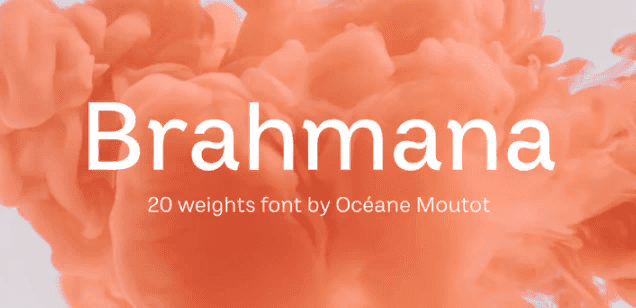
Название: Brahmana Font (2021)
Brahmana - это современный шрифт sans serif, отличающийся игривостью и оригинальными деталями.
Его большая высота x-height обеспечивает этому дружелюбному линейному шрифту разнообразие для использования, от заголовков, издания текстов, брендинга, журналов и так далее. Большое разнообразие глифов, включая акценты, цифры старого стиля и лигатуры, придадут уникальность вашим дизайнам.
Brahmana доступен в 20 стилях, от тонкого до тяжелого, в романском и курсивном начертании.
Название: Brahmana Font (2021)
Brahmana - это современный шрифт sans serif, отличающийся игривостью и оригинальными деталями.
Его большая высота x-height обеспечивает этому дружелюбному линейному шрифту разнообразие для использования, от заголовков, издания текстов, брендинга, журналов и так далее. Большое разнообразие глифов, включая акценты, цифры старого стиля и лигатуры, придадут уникальность вашим дизайнам.
Brahmana доступен в 20 стилях, от тонкого до тяжелого, в романском и курсивном начертании.